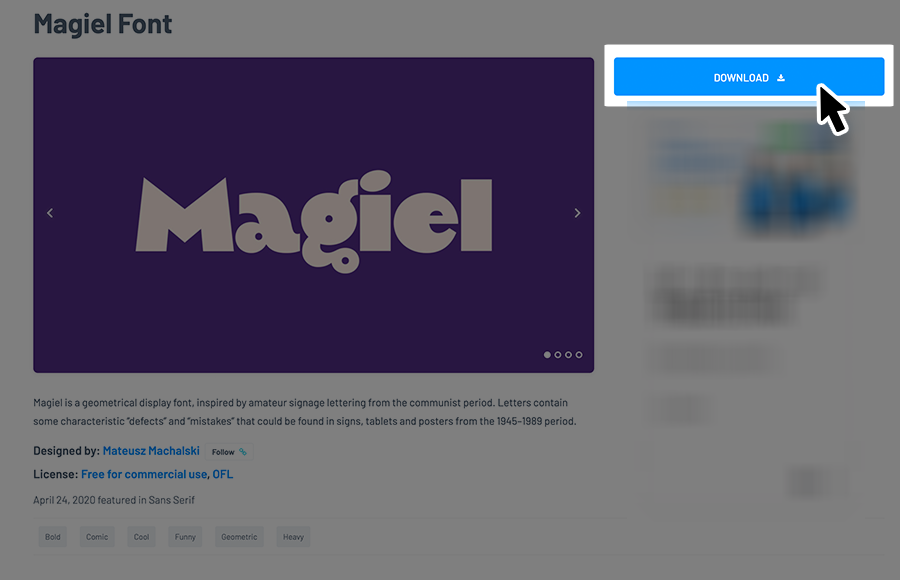
Magielフォントは、丸みと極太感を兼ね備えたポップなサンセリフ書体です。
ふっくらとした字形が親しみやすく、ユーモラスな形状がクセになるようなフォントです。太い線と細い線のギャップが面白く、太めのウェイトでも重たくなりすぎず、バランスのよいシルエットにまとまっています。
無邪気さを感じられるフォントなので、キッズ向けコンテンツやポップな広告、キャラクター系のロゴなどに使いやすいフォントです。大きく配置すると存在感が増し、カラフルな配色とも相性が良いため、明るく楽しい雰囲気をつくりたい場面に活躍するフォントです。
| 作者 | Mateusz Machalski |